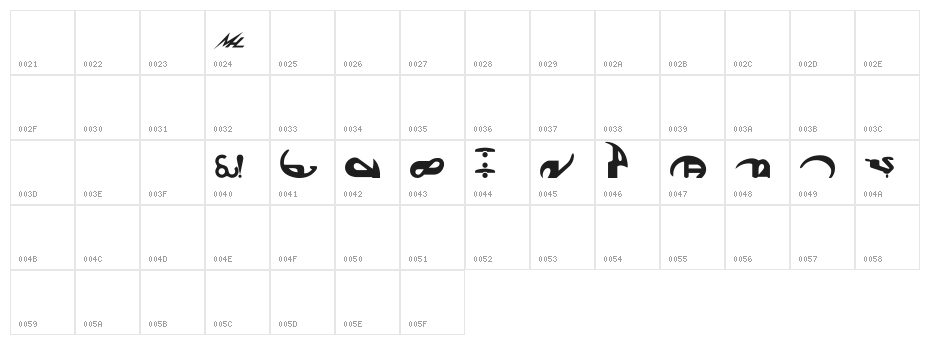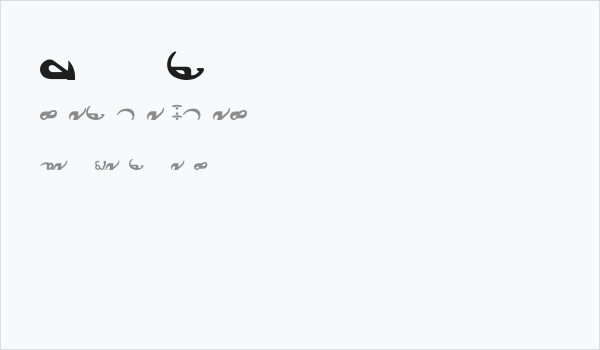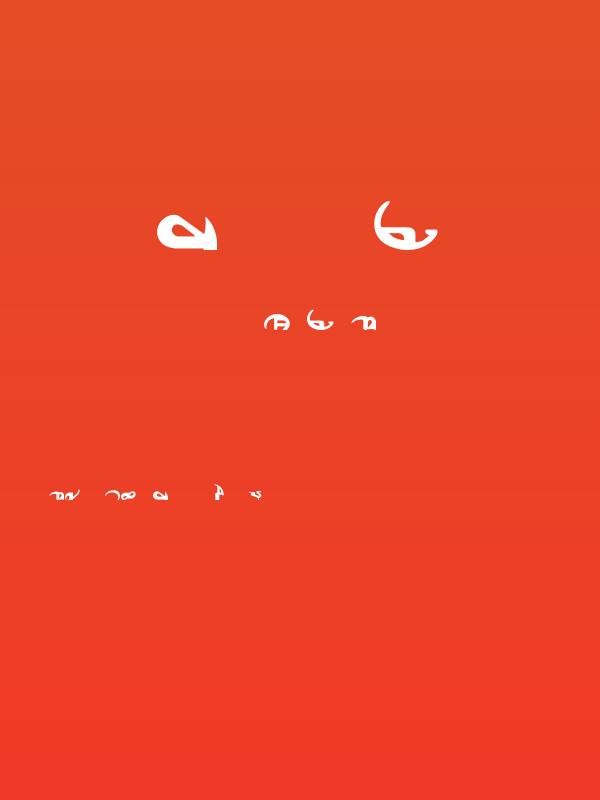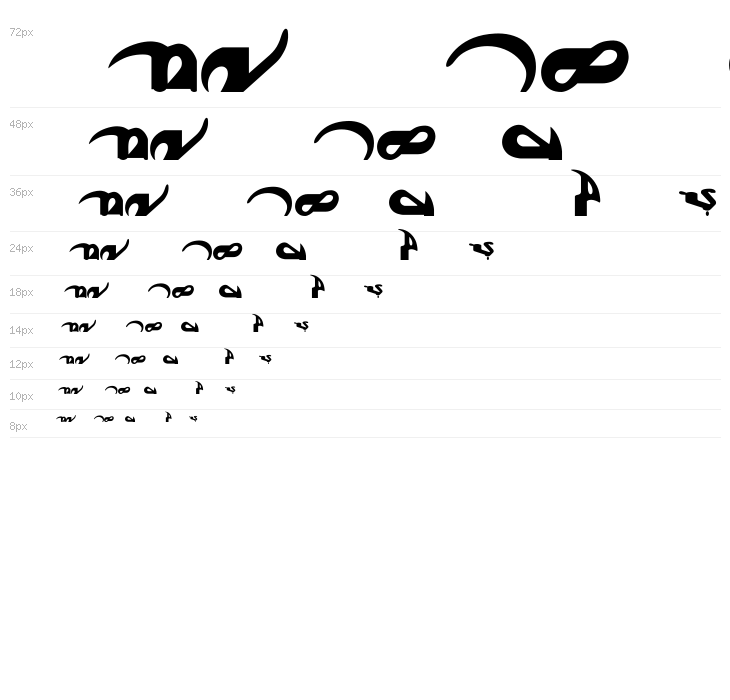
Boonta Font
| Stil general | Futuristic, Alien |
| Caz de utilizare | Logos, Posters, Titles |
| Proiecte propuse | Ideal for sci-fi themed designs, video game interfaces, movie posters, or any project needing a unique, extraterrestrial aesthetic. |